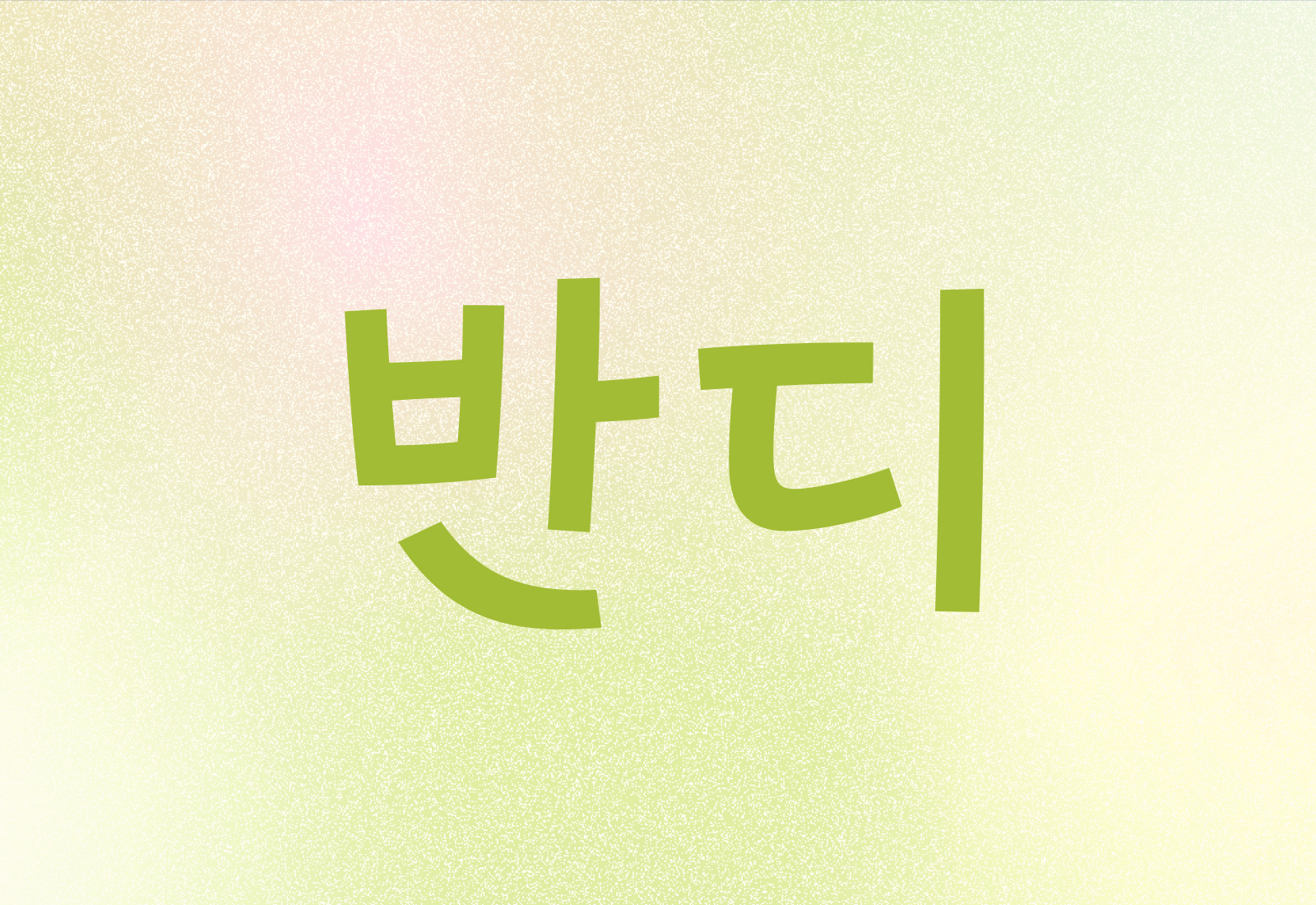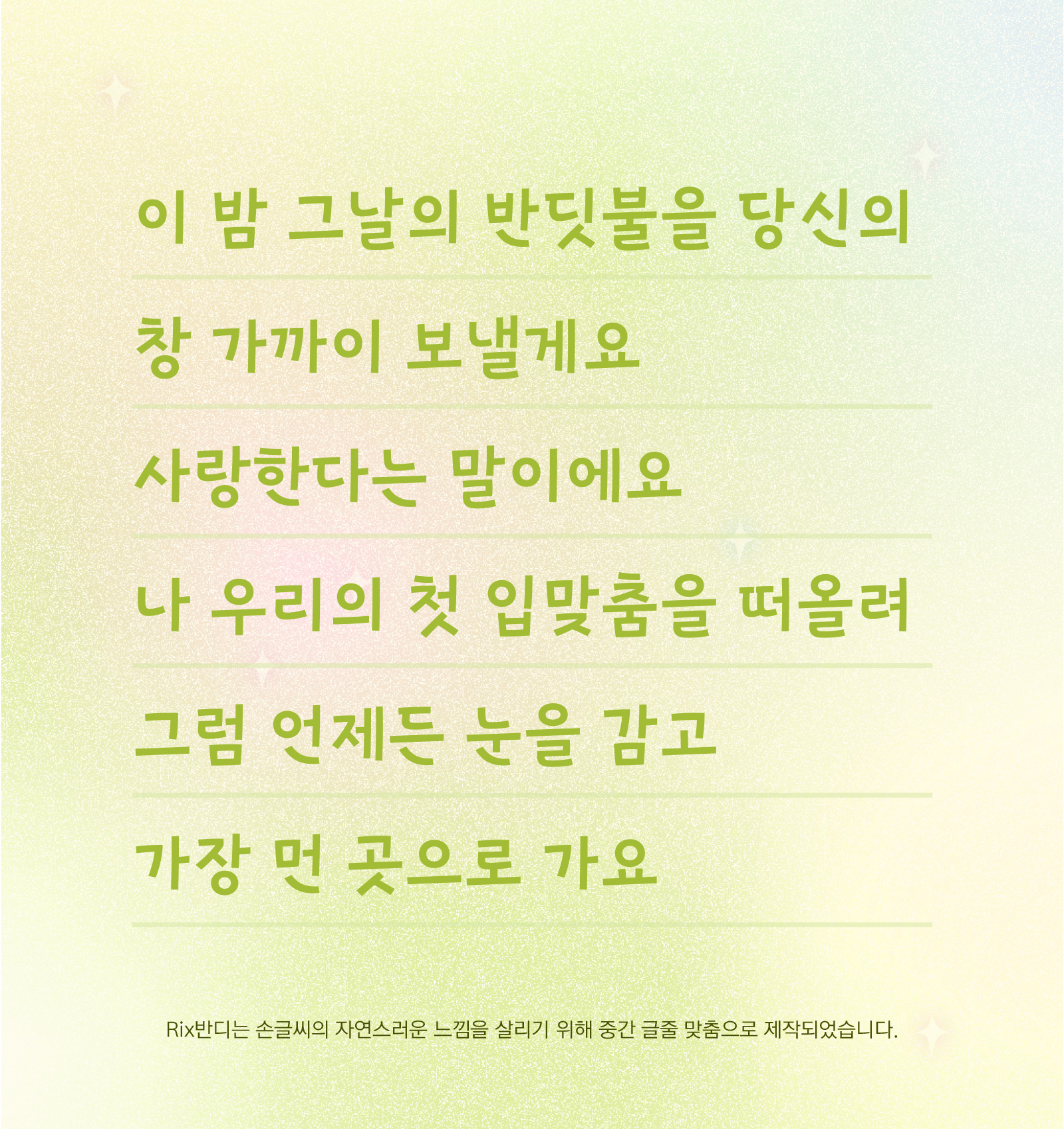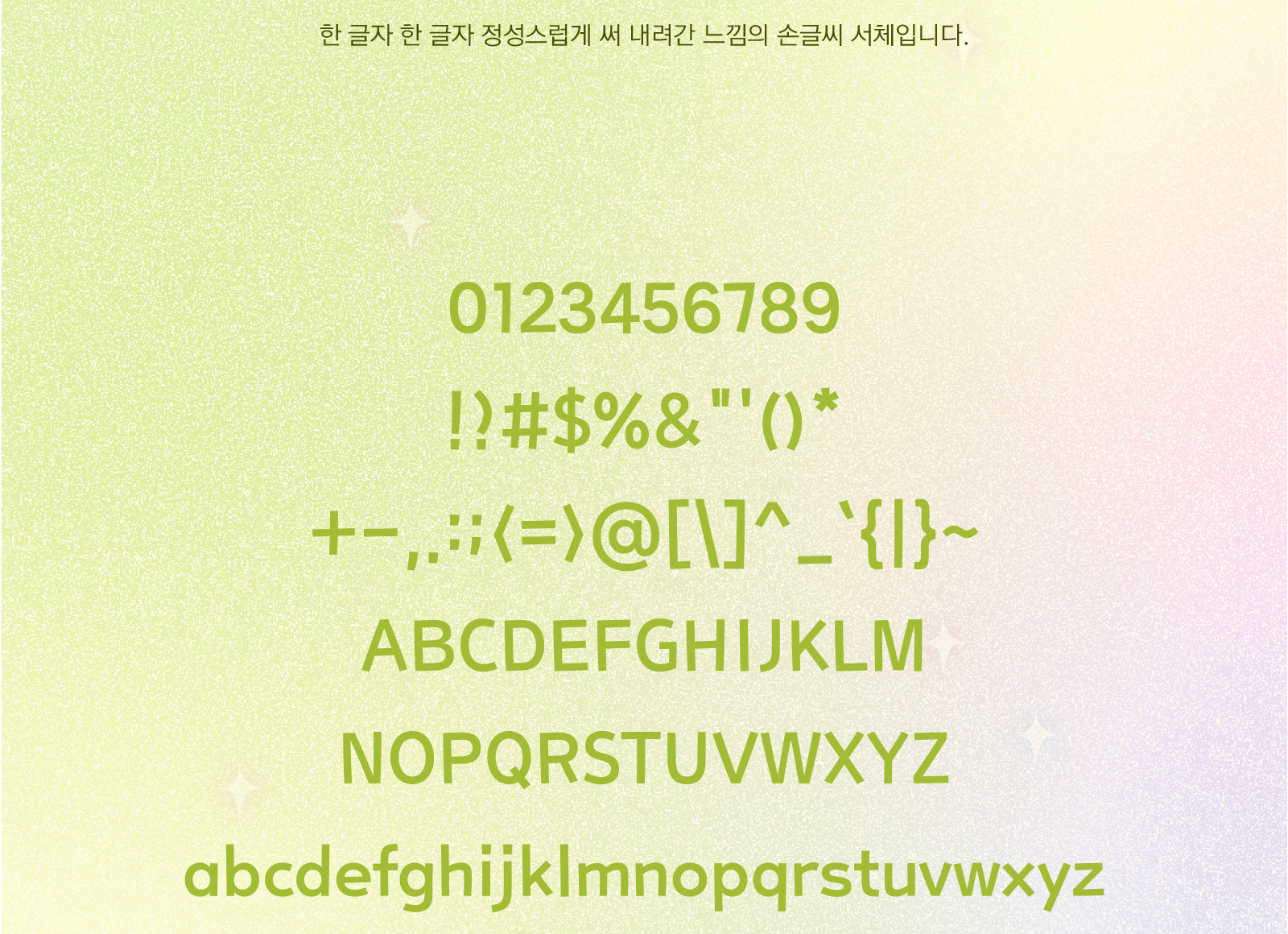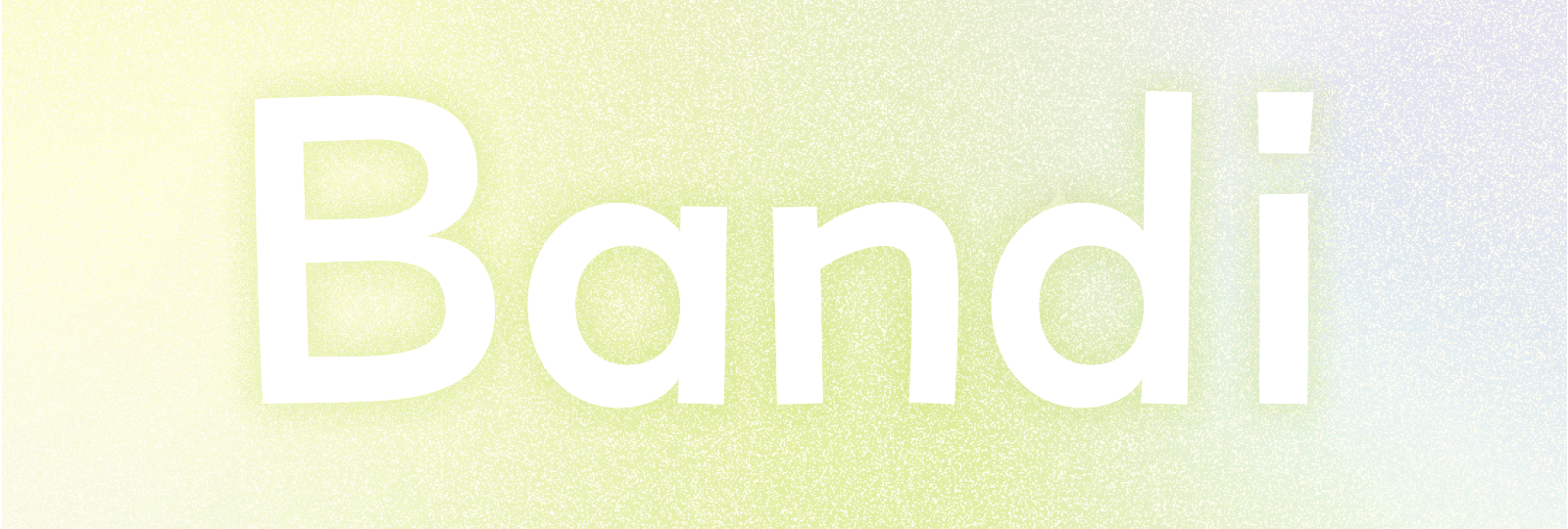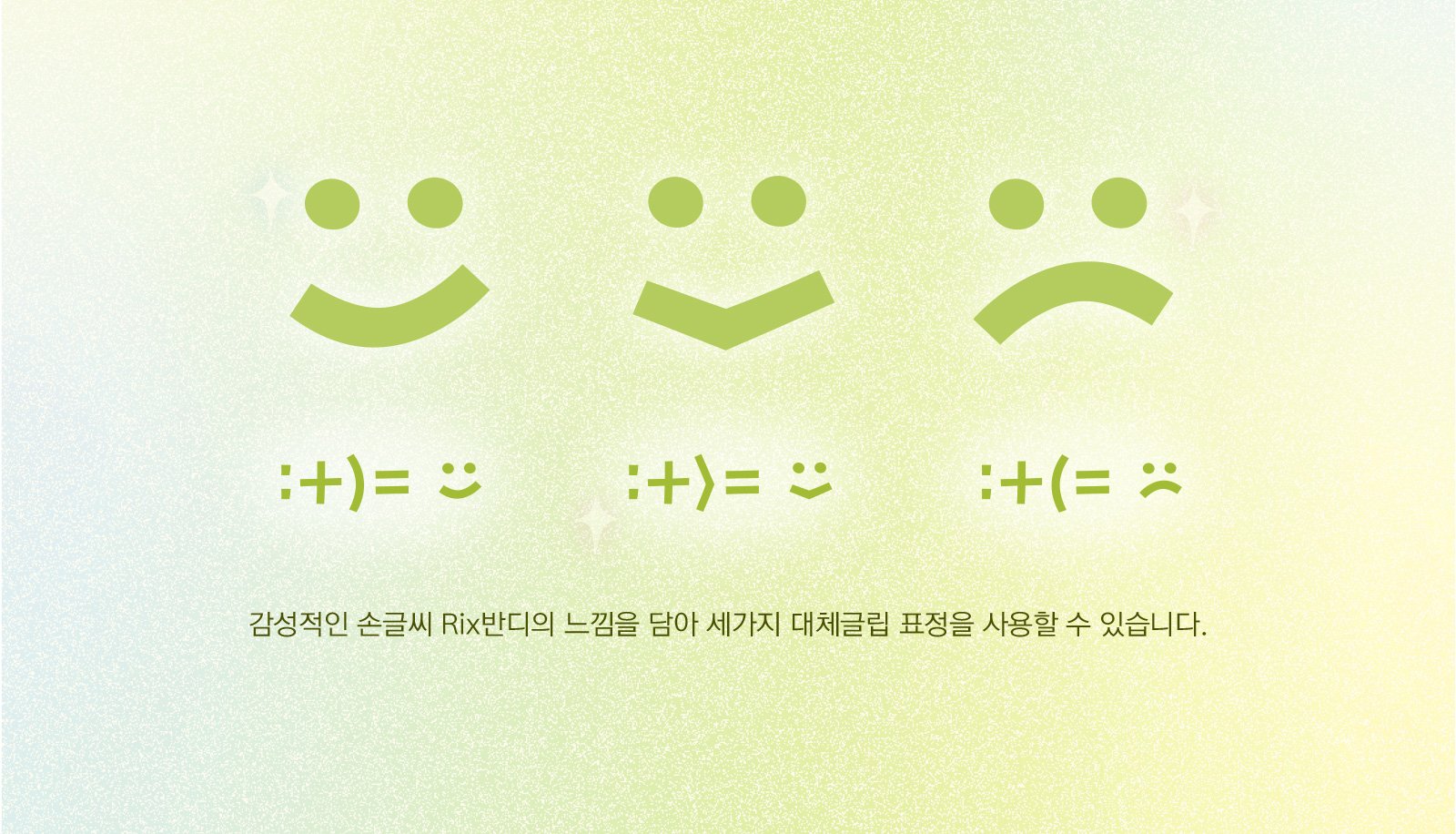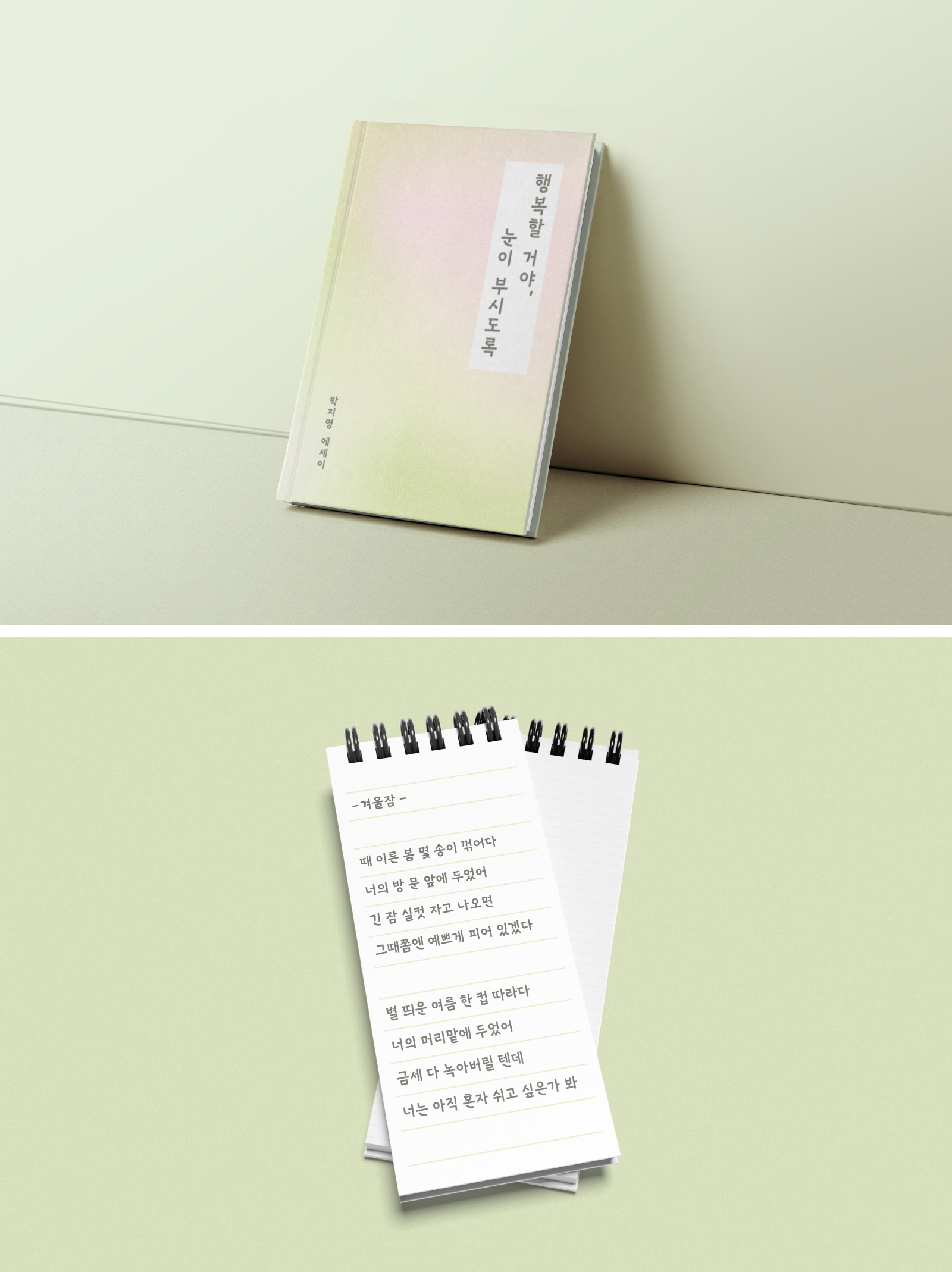
Rix반디
1 종 - SemiBold
Rix반디는 한 글자 한 글자 정성스럽게 쓴 잔잔하고 감성적인 손글씨로,
부드럽고 자연스러운 획이 따뜻한 느낌을 담고 있습니다.
폰트명 Rix반디 / RixBandi
폰트디자인 이수하
폰트구성 한글 2,350자 + 추가자 430자 / 라틴 94자 / 약물 986자
꽃처럼 피어나 별처럼 빛나는 그대에게